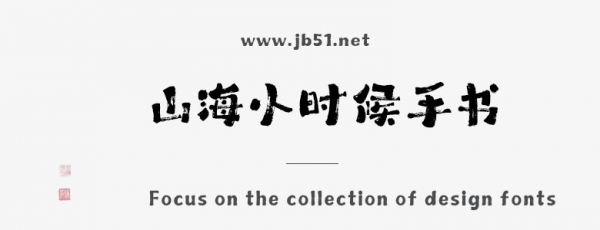
山海小時(shí)候手書(shū) W是由山海字庫(kù)出品的字體,這款字體筆觸略粗,具有很好的視覺(jué)感,適合應(yīng)用于藝術(shù)設(shè)計(jì)、平面宣傳設(shè)計(jì)、網(wǎng)頁(yè)設(shè)計(jì),書(shū)法字帖等領(lǐng)域,需要的朋友可以前來(lái)本站下載。